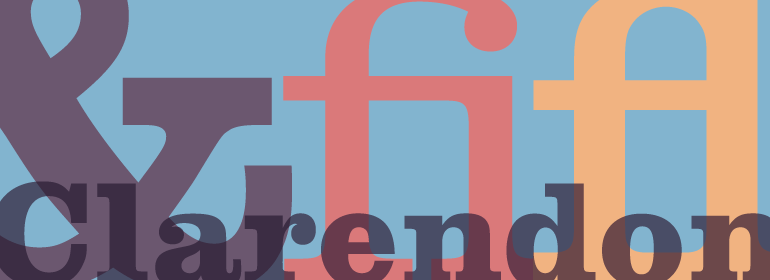
Monotype Clarendon®
Monotype Clarendon®,这款字体结构工整、笔画清晰,兼顾美观与易读性,适用于标题、正文、海报、包装、LOGO 等多种场景。字形优雅稳定,风格百搭耐看,适配日常排版与创意设计,让文字呈现更舒适、更具质感。Monotype Clarendon®一笔一画,皆是细节,以均衡的比例、流畅的线条打造舒适视觉体验,字形端正大气,风格简约现代。无论是商业设计、品牌宣传还是日常排版,都能轻松驾驭,让文字更有格调与力量。Monotype Clarendon®字体下载。